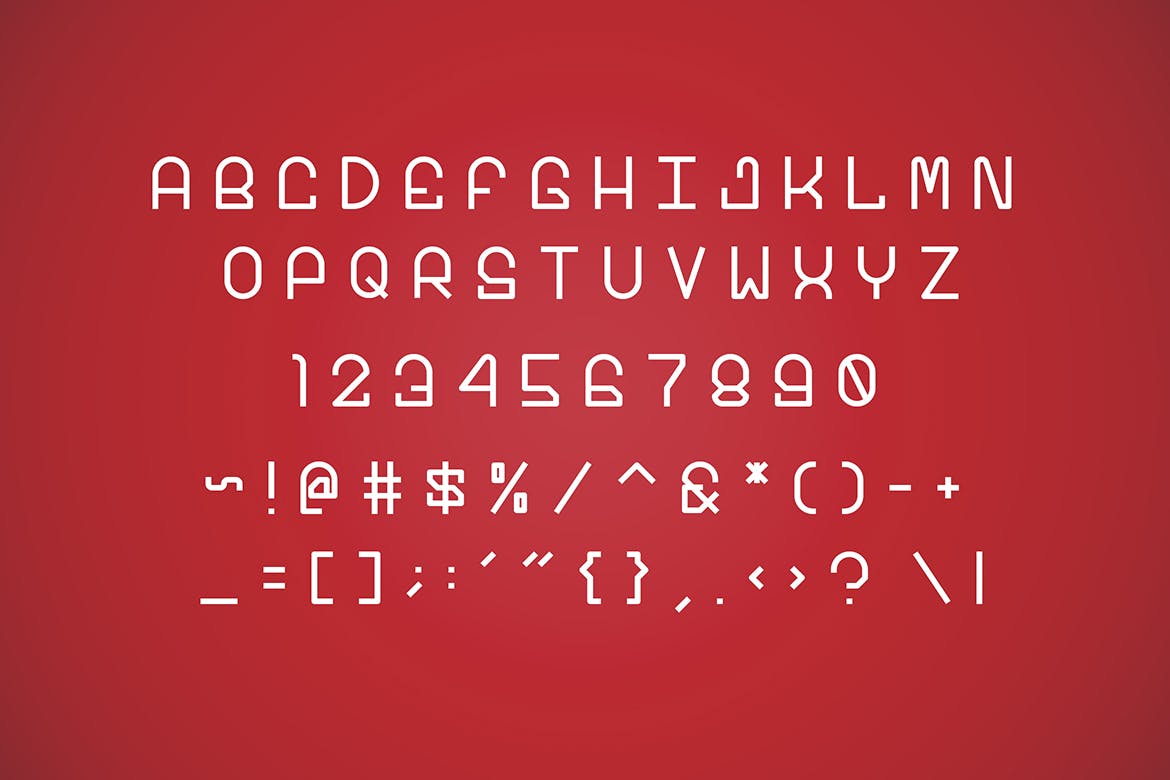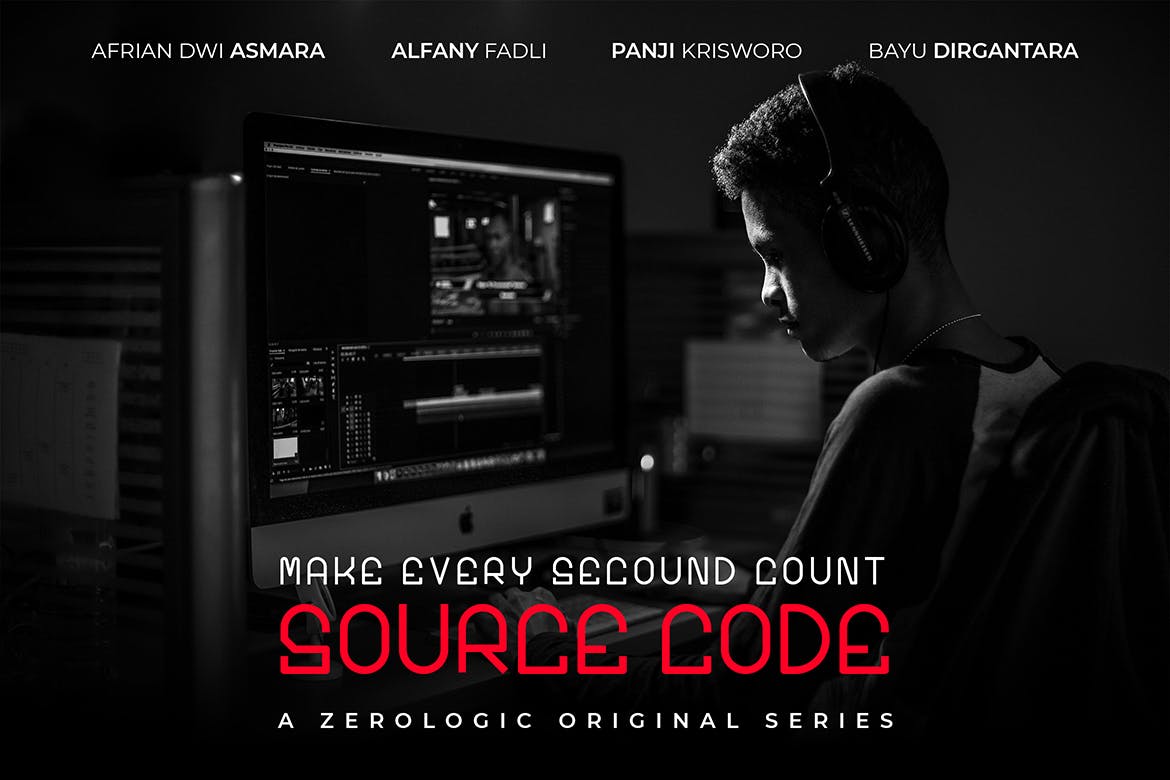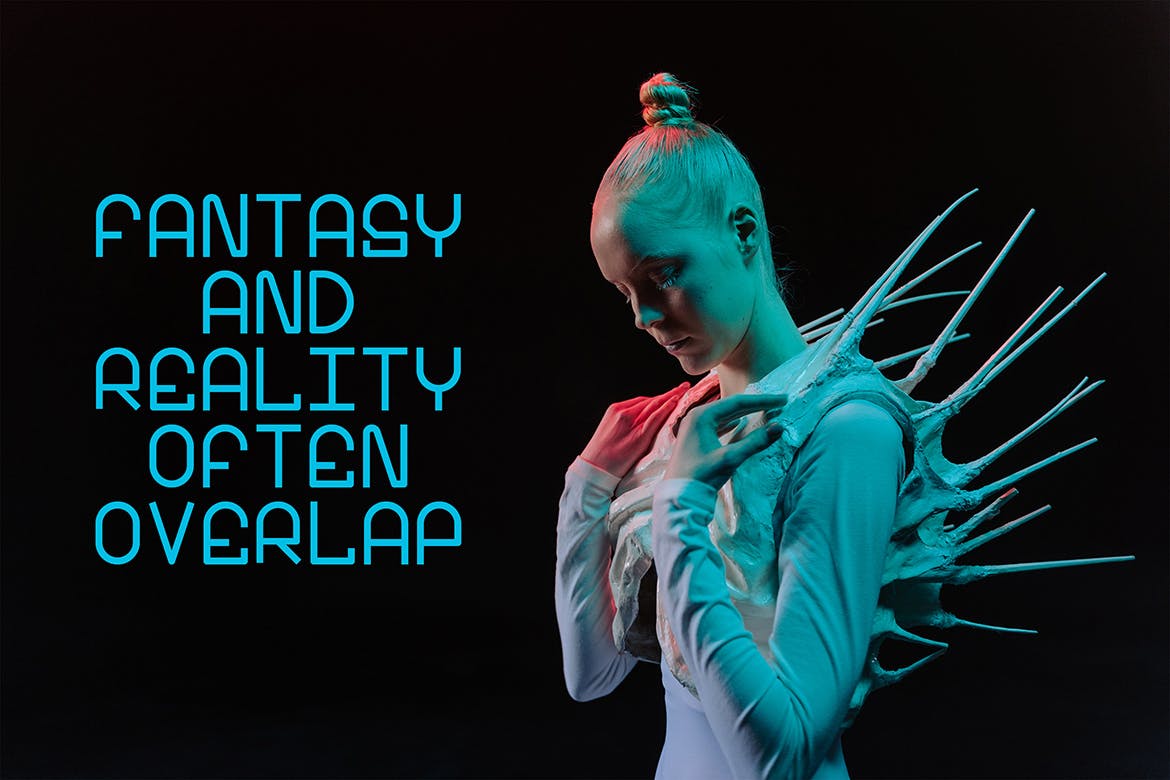
فونت Angie یک فونت مدرن است که با طراحی منحصر به فرد برای نیازهای شما ایجاد شده است. این فونت خنک با حروف بزرگ، کوچک، اعداد و نمادها کامل است. این فونت بسیار قوی و تیز برای عناوین، تایپوگرافی، پوسترها، مجلات، بروشورها، بستهبندی، وبسایتها و بسیاری دیگر از پروژههای طراحی شما عالی است و طراحیهای شما را جذابتر میکند.